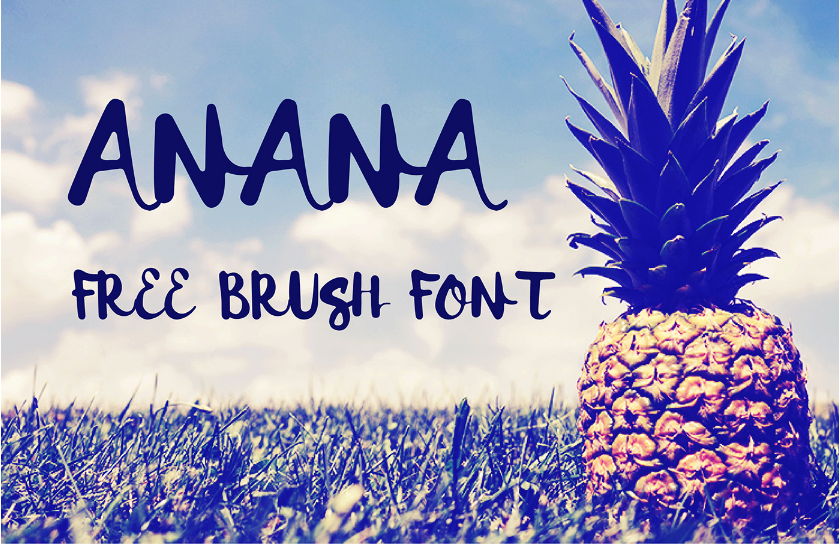
Anana Brush Font – Fonte Grátis
Anana Brush Font
Anana Brush é uma fonte script desenvolvida pelo designer Hamilton que traz características do desenho à mão livre. Essa fonte é não apenas algo especial e criativo, mas também totalmente gratuita, permitindo a sua utilização comercial sem limitações. Embora esteja disponível de forma gratuita, é um gesto respeitoso sugerir um pequeno contributo para o designer em uma das direções abaixo fornecidas, reforçando assim seu apoio à criação artística e ao mundo do design gráfico que ele abraça. Anana Brush oferece um toque autêntico e elegante, perfeito para adicionar um toque personalizado aos seus projetos. Com sua disposição fluida e elegante, a fonte é uma excelente escolha para aquelas criações onde o seu estilo e grafição natural são particularmente apreciados.